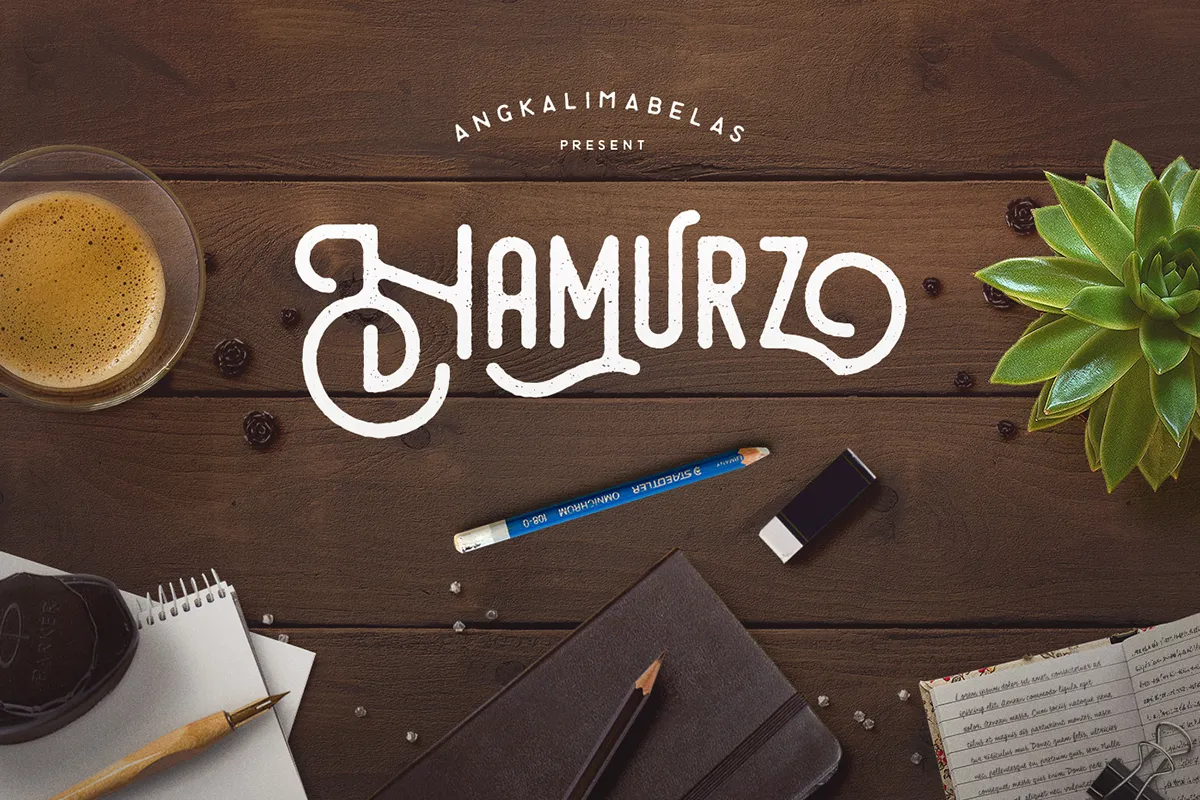
Hamurz Font – Download Grátis
A Hamurz é uma fonte blackletter criada pelo designer Hamilton. Essa família de letras oferece um toque elegante e sombrio que pode adicionar um charme único a qualquer projeto gráfico, seja ele para um site profissional ou um livro de arte. Com suas linhas arredondadas e detalhes elaborados, a Hamurz traz uma atmosfera única e envolvente ao texto, adequando-se perfeitamente aos elementos de design que exigem um toque antiquado ou formal. Para aqueles que desejam experimentar o premium version desta fonte, Hamilton disponibilizou uma ligação direta para download em seu marketplace oficial. A Hamurz é mais do que uma simples fonte; ela é um recurso gráfico singular, capaz de transformar qualquer projeto em algo impressionante e único.